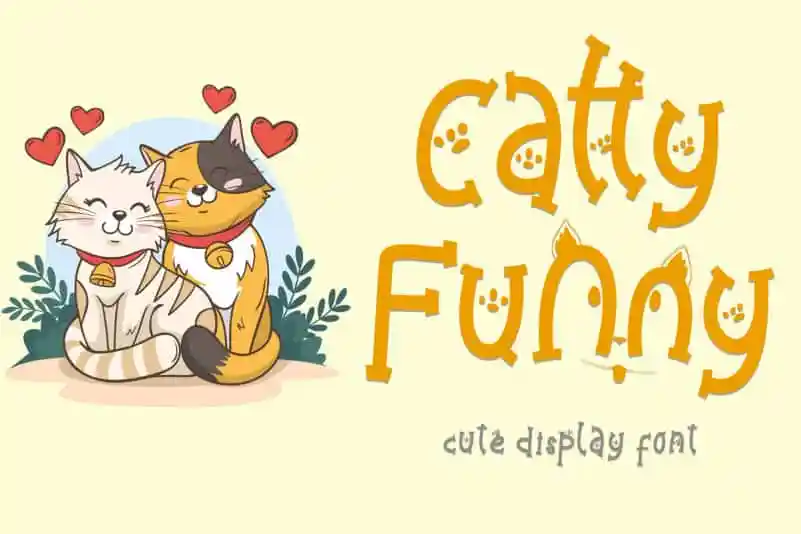
Catty Funny Display Font
A Catty Funny Display Font é uma fonte visualmente atraente e única perfeita para aqueles que desejam trazer um toque divertido ao seu design. O principal objetivo desta fonte é facilitar a utilização, pois foi projetada especificamente para ser fácil de usar. Seu design minimalista mas divertido permite aplicá-la em uma vasta gama de materiais e ideias de criação gráfica, desde o design de roupas até os ambientes digitais. A Catty Funny é uma fonte adequada para promover produtos como pet food, criar posteres e t-shirts, desenhar capas de livros e logotipos. Suas formas divertidas e personalizadas permitem que você personalize qualquer projeto gráfico em suas mãos, tornando-a perfeitamente adaptável a uma variedade de formatos: desde banner publicitário até capa de livro infantil. Com uma aparência delicada e fácil de entender, esta fonte se destaca como um recurso visual para designers que desejam trazer um toque diferente ao seu trabalho. Ideal tanto para quem deseja criar designs mais leves quanto para aqueles que desejam adicionar um pouco de personalidade a seus materiais digitais ou impressos.